3 Mẫu Font Handwriting Việt Hóa Miễn Phí
Font Handwriting việt hóa là font chữ rất được mọi người ưa chuộng, không chỉ trong thiết kế design mà cả trong marketing hay giáo dục… Hãy lựa chọn ngay cho mình 1 mẫu font Handwriting đã được việt hóa trong bài biết dưới đây nhé.
Giới thiệu về font Handwriting việt hóa
Sự khác biệt giữa handwriting font việt hóa và chữ viết tay có lẽ hơi sai ngữ pháp nhưng dựa trên thực tế là handwriting font việt hóa có bản chất trang trí hoặc thư pháp, trong khi handwriting font việt hóa thực sự phản ánh kỹ thuật mà người ta sẽ sử dụng trong một bức thư. Ví dụ về handwriting font việt hóa bao gồm FF Mr. K, ITC Zemke Hand và Cavallini.
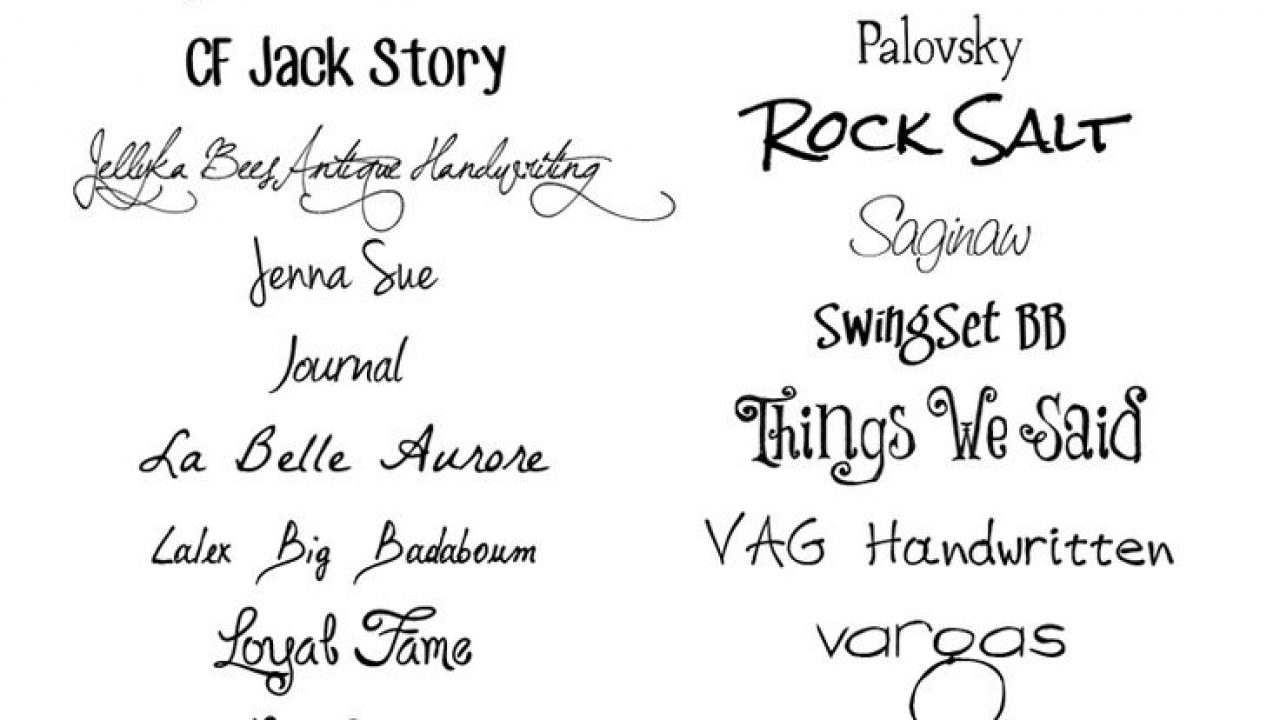
Viết tay là thứ có thể xa vời với rất nhiều người trong thế giới số hóa ngày nay nhờ các thiết bị điện tử khác nhau, và không lạ khi chúng ta phải bắt gặp những tờ Times New Roman hay Verdana nhàm chán, dù chỉ nhận được một lời chào.
Font handwriting việt hóa hữu ích cho biểu trưng, ​​tiêu đề, ghi chú, tuy nhiên không phải cho nội dung thông thường. giống như một công thức được viết ra vội vã và được viết ra ngay lập tức. Kiểu văn bản có đầy đủ các trọng âm để bạn có thể sử dụng nó trong một công việc đa ngôn ngữ.
Tính năng nổi bật của font handwriting việt hóa
Trên thực tế, có một số lợi thế của việc sử dụng handwriting font việt hóa. Thứ nhất, handwriting font việt hóa thêm dấu ấn cá nhân, điều này đúng đặc biệt khi bạn đang gửi thiệp, lời mời bằng cách sử dụng chúng. Thứ hai, handwriting font việt hóa sẽ thu hút ánh nhìn. Hãy tưởng tượng sử dụng handwriting font việt hóa thay vì phông chữ an toàn trên web như Arial, Times New Roman cho tiêu đề blog, tiêu đề bài đăng, v.v., chắc chắn sẽ gây ấn tượng tới người đọc.
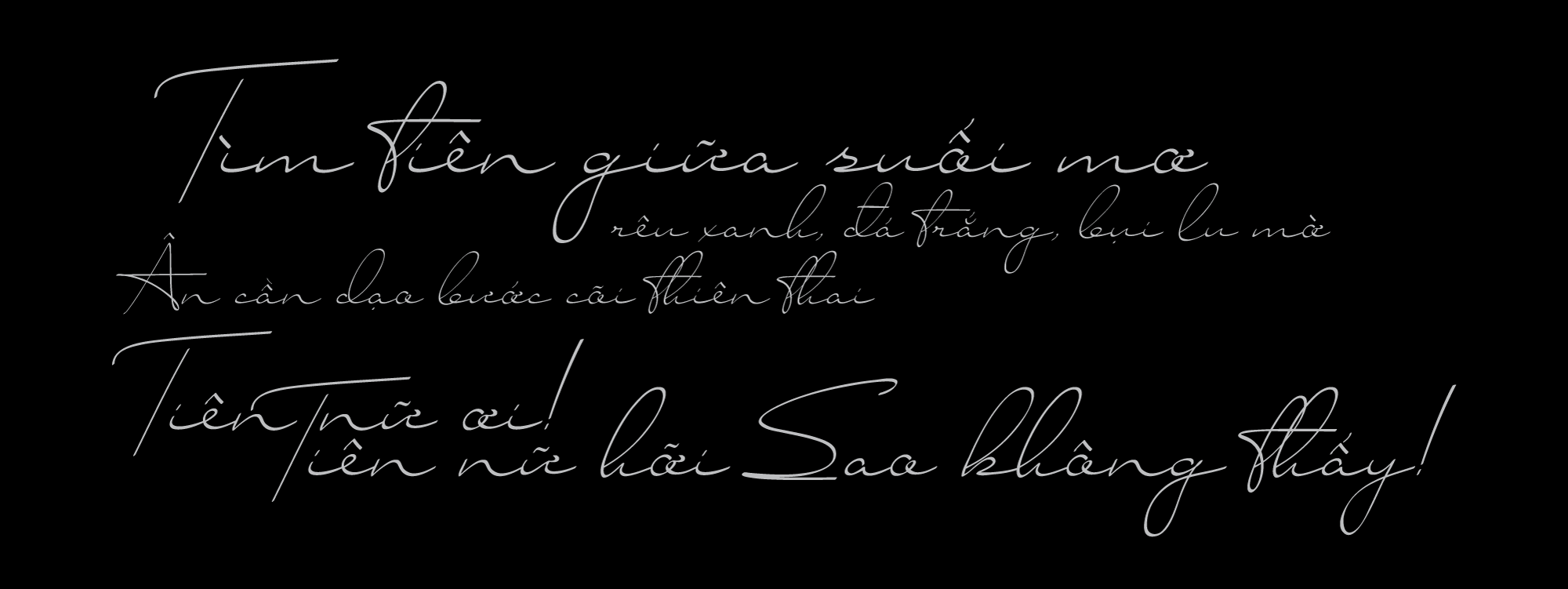
Phông chữ viết tay tốt cho logo, tiêu đề, ghi chú nhưng không tốt cho văn bản thông thường. Hasty Tasty được tạo ra bởi David Kerkhoff là một phông chữ điển hình trong phong cách viết tay. Đúng như tên gọi của nó, Hasty Tasty trông giống như một công thức được viết vội, ghi nhanh vào một ghi chú. Phông chữ có đầy đủ các điểm nhấn để bạn có thể sử dụng nó trong một dự án đa ngôn ngữ.
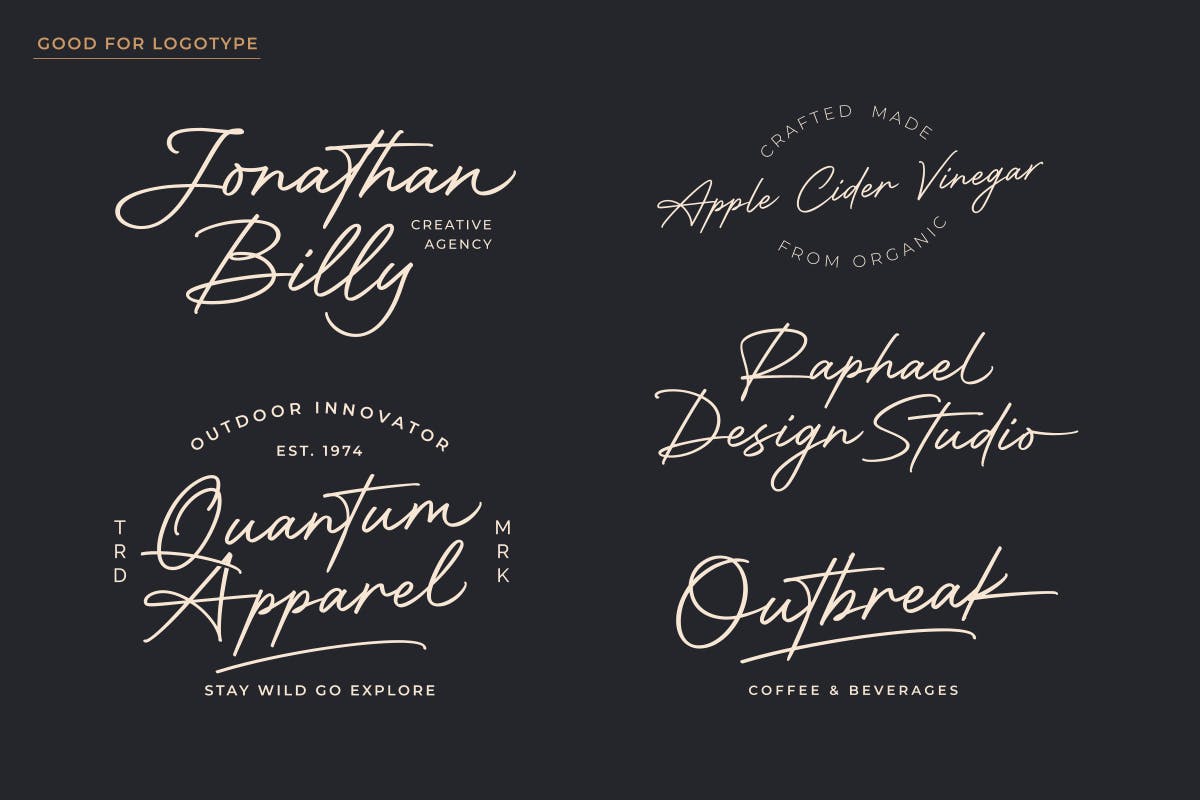
3 font handwriting Việt hóa tốt nhất
1. Hasty Tasty của David Kerkhoff
Hurried Tasty do David Kerkhoff thực hiện là một kiểu văn bản phổ biến trong kiểu viết tay. Đúng như tên gọi của nó, Hasty Tasty giống như một công thức được viết ra vội vã và được viết ra ngay lập tức. Kiểu văn bản có đầy đủ các trọng âm để bạn có thể sử dụng nó trong một công việc đa ngôn ngữ.
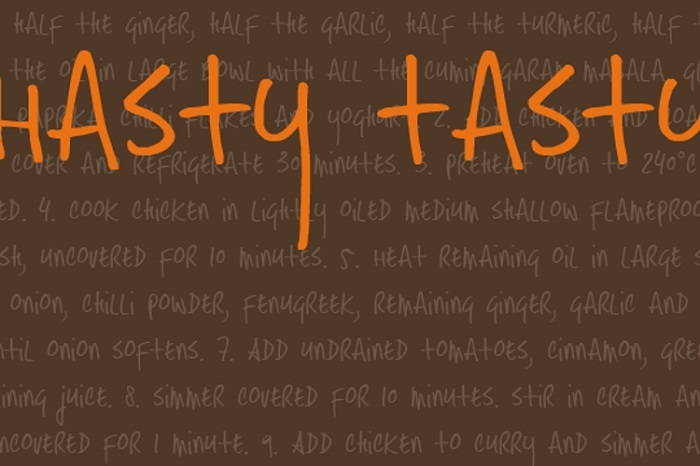
2. Beatrix Signature Font
Font chữ này rất thích hợp với những chữ ký, để tạo được chữ ký cho riêng mình. Với sự kết hợp của các ký tự ngắn và dài, phông chữ này rất phong cách và đường nét tự nhiên. Sử dụng phông chữ này làm chữ ký của mình hoặc dùng thử trên bao bì và logo thì rất phù hợp.
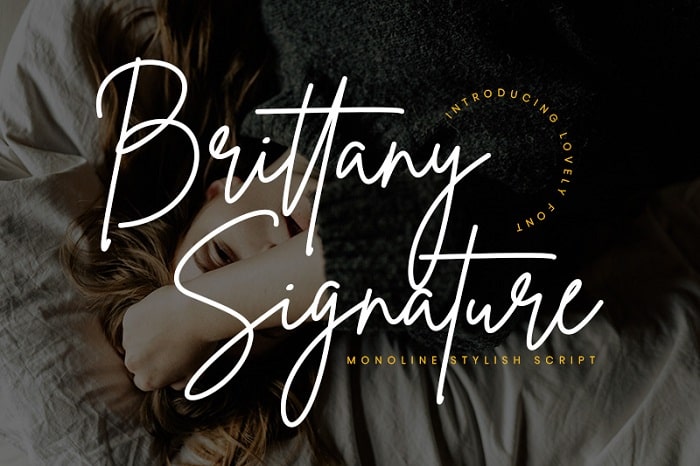
3. Amstenia Typeface
Các kiểu chữ Amstenia giống với các ký tự vẽ tay xuất hiện ở một góc nhỏ. Dùng chữ này để làm tên bảng hiệu cửa hàng của bạn hoặc dùng viết  trên blog của mình để blog nhìn mới mẻ!